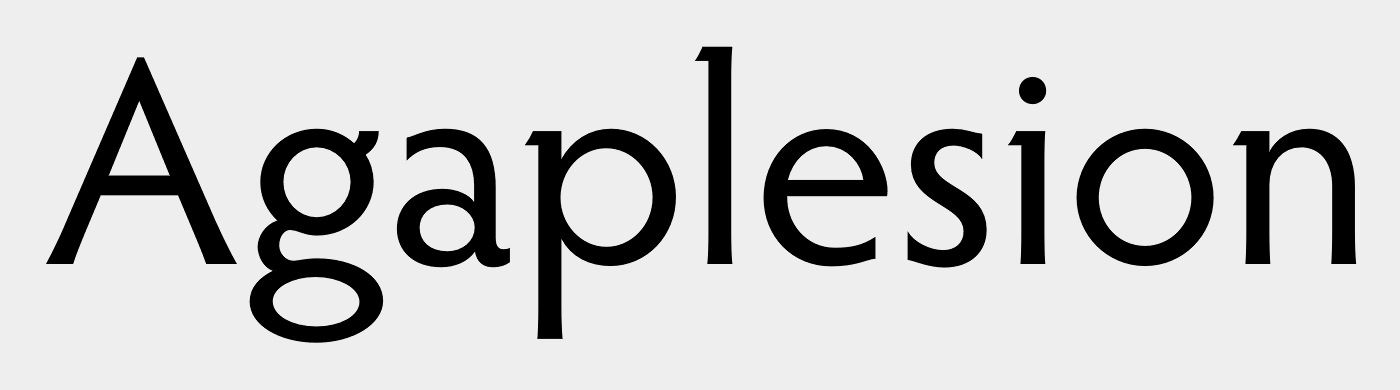
Typo für eine Krankenhaus
Ich suche eine Font für ein Krankenhaus, welches auf einer christlichen Tradition basiert. Sie sollte einfach und klar sein, sowie freundlich wirken. Sie darf gern etwas traditionelles haben, sollte dennoch modern und freundlich sein.
Hat jemand and eine Idee oder Tipps zur Inspiration? Mir fällt dieser Spagat zwischen Tradition und Moderne schwer und bin über jede Hilfe dankbar.
Suchst du die Schrift für den werblichen Auftritt oder für das Wegeleitsystem?
Danke für deinen Tipp :) Die Schrift ist wirklich schön, aber ich finde sie etwas zu spitz für mein jetziges Projekt. Vielleicht passt sie ja ein anderes mal besser.
Danke für eure Nachricht. Ich habe mir schon sehr viel angeschaut, aber irgendwie bin ich nicht zufrieden. Im Moment habe ich die ITC Clearface als Headline in Kombination mit Futura für die  Fließtexte eingesetzt. Die ist mir aber viel zu starr und unfreundlich. Ich hätte gern einen persönlicheren Touch, mehr Dynamik. Allerdings brauche ich im Idealfall eine Schrift, welche auch für ein später entwickeltes Leitsystem passt.
Ich persönlich würde mir mal humanistische (dynamische) Serifenlose mit warmen Charakter ansehen. Da hast Du die Tradition im Skelett (Ableitung Antiqua) und das Serifenlose für die Moderne.
Möglicherweise etwas in diesem Spektrum:
Eine starre Geometrische wie die Futura wäre mir auch viel zu unterkühlt, wenn ich da Patient sein müsste. Außerdem wäre ich damit auch für die Leitsystem-Option nicht so glücklich.